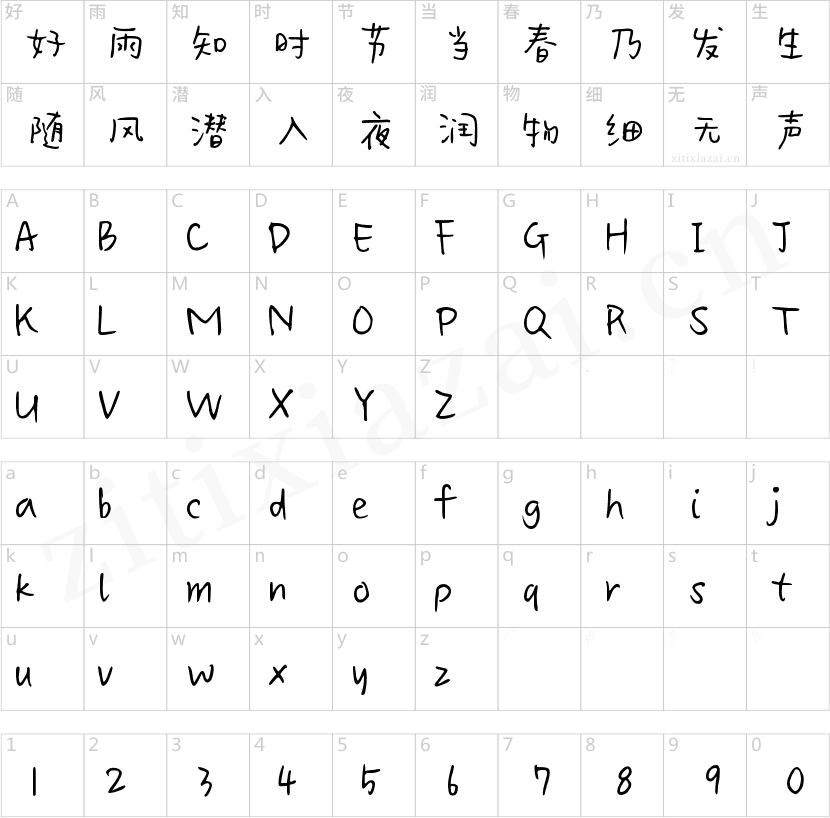
Aa余生共白首
Aa余生共白首字体
Aa余生共白首是一款非常具有艺术性的字体,它的设计灵感来源于对古典艺术的研究,同时又融入了现代字体设计的元素。字形优美,笔画粗细变化自然,给人以大气、典雅的感觉。Aa余生共白首是一款既传统又现代的字体,它的设计充满艺术感,美观大方,实用性也非常强。无论是对于设计师还是对于普通读者来说,都是一种非常不错的字体选择。Aa余生共白首适合用于具有艺术感的场合,比如海报、宣传单张、书籍封面等。由于其字形流畅且具有动态感,也适合用于大量的文本排版,如报纸、杂志等。